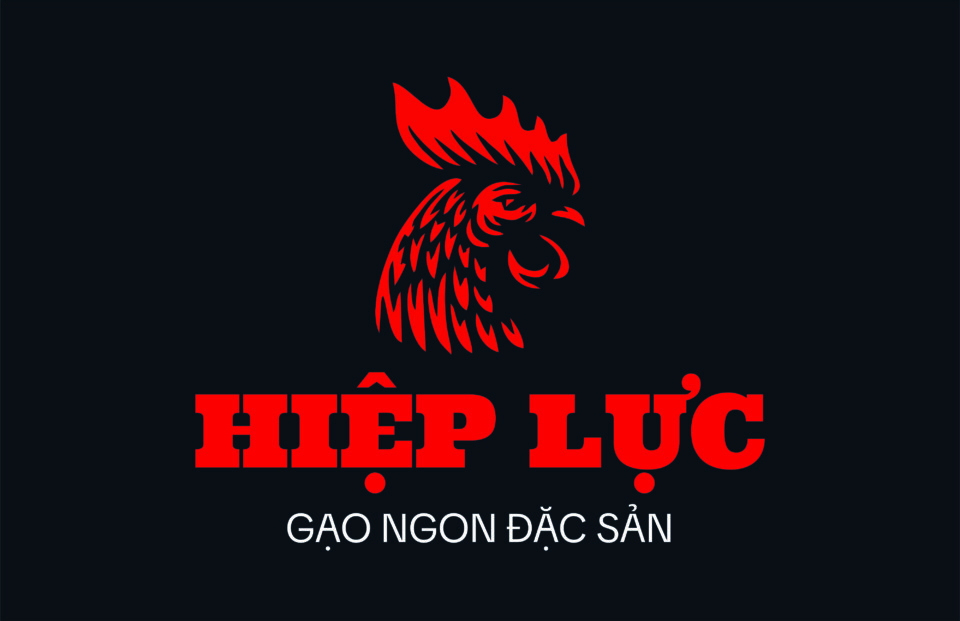
Font Việt hóa VN Ultra
Giới thiệu về bộ Font Việt hóa VN Ultra trong thiết kế đồ họa
Trong thế giới thiết kế hiện đại, việc tìm kiếm một bộ Font Miễn Phí chất lượng và hỗ trợ đầy đủ tiếng Việt luôn là ưu tiên hàng đầu của các bạn học sinh, sinh viên và thầy cô giáo. Font Việt hóa VN Ultra nổi lên như một giải pháp hoàn hảo, đáp ứng được cả yêu cầu về thẩm mỹ lẫn tính ứng dụng cao. Đây là bộ phông chữ được tinh chỉnh kỹ lưỡng về dấu câu, giúp loại bỏ hoàn toàn lỗi hiển thị khi soạn thảo văn bản hay làm bài thuyết trình. Sự xuất hiện của Font Việt hóa VN Ultra giúp các bài giảng điện tử và báo cáo học tập trở nên chuyên nghiệp, thu hút hơn bao giờ hết.
Đặc điểm nổi bật của bộ phông chữ VN Ultra
Đặc trưng lớn nhất của Font Việt hóa VN Ultra chính là độ dày nét chữ (weight) vô cùng mạnh mẽ và rõ ràng. Khác với các kiểu chữ mảnh dẻ thông thường, dòng Ultra mang lại cảm giác chắc chắn, tạo điểm nhấn thị giác cực tốt cho các tiêu đề lớn. Các ký tự được thiết kế với khoảng cách hợp lý, đảm bảo dù bạn phóng to hay thu nhỏ thì chữ vẫn giữ được độ sắc nét. Bên cạnh đó, tính tương thích của bộ font này với các phần mềm phổ biến như Microsoft Word, PowerPoint hay Canva là một điểm cộng lớn giúp người dùng dễ dàng thao tác mà không cần kỹ thuật phức tạp.
Ứng dụng thực tế của Font Việt hóa VN Ultra trong môi trường giáo dục
Đối với học sinh, Font Việt hóa VN Ultra là công cụ tuyệt vời để trang trí bìa tiểu luận hoặc làm các tấm thiệp chúc mừng thầy cô. Font chữ này không chỉ giúp nội dung nổi bật mà còn thể hiện sự chỉn chu, sáng tạo của người thực hiện. Trong khi đó, các thầy cô giáo có thể tận dụng bộ font này để thiết kế các bảng tin lớp học, các tiêu đề bài giảng trên lớp nhằm thu hút sự chú ý của học sinh. Việc sử dụng một phông chữ đẹp và chuẩn Việt hóa như Font Việt hóa VN Ultra giúp thông tin được truyền tải mạch lạc, không gây khó chịu cho mắt người đọc.
Kết luận về giá trị của bộ Font Việt hóa VN Ultra